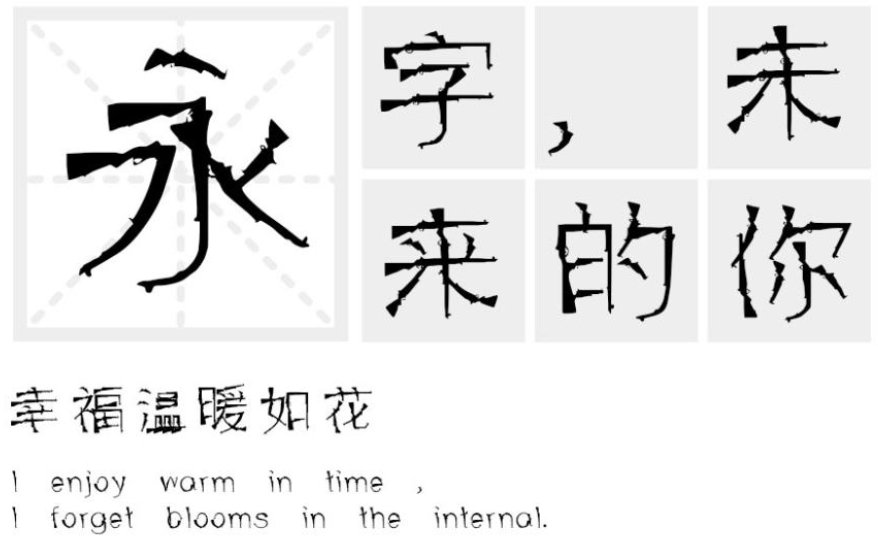
汉标老枪体是一款非常独特有趣的电脑中文艺术字体,该字体给人的第一眼看上去就是字体的框架是由一把把枪连接起来的,看上去非常的有亮点。将字形中的点、撇、捺、钩、提等笔画各具面目,笔画运用了老枪图形元素来构建,把这些笔画做成了老枪,概括为飘逸的老枪,并且使左右舒展的笔画尽量对称,最大限度地简化笔画老枪造型。
字体名称:汉标老枪体
字体类别: 创意字体 艺术字体